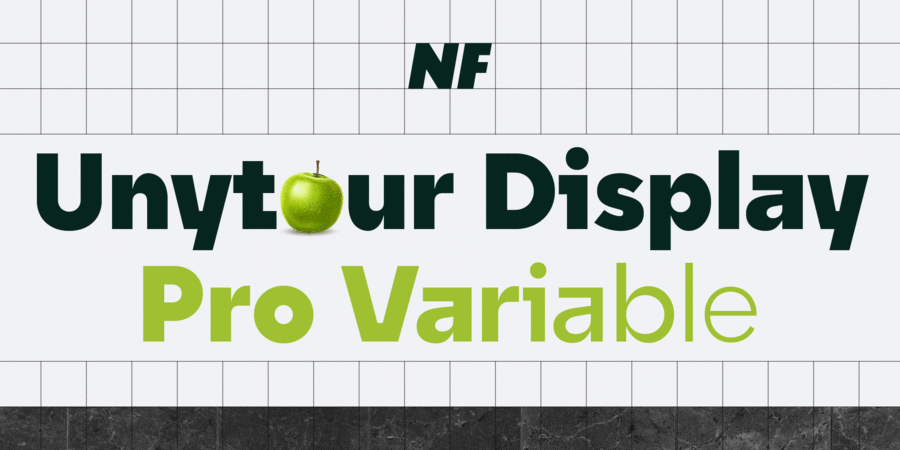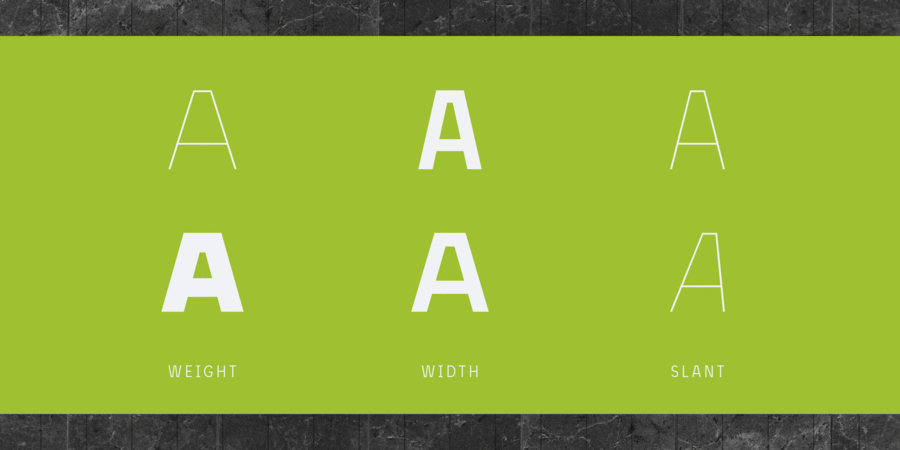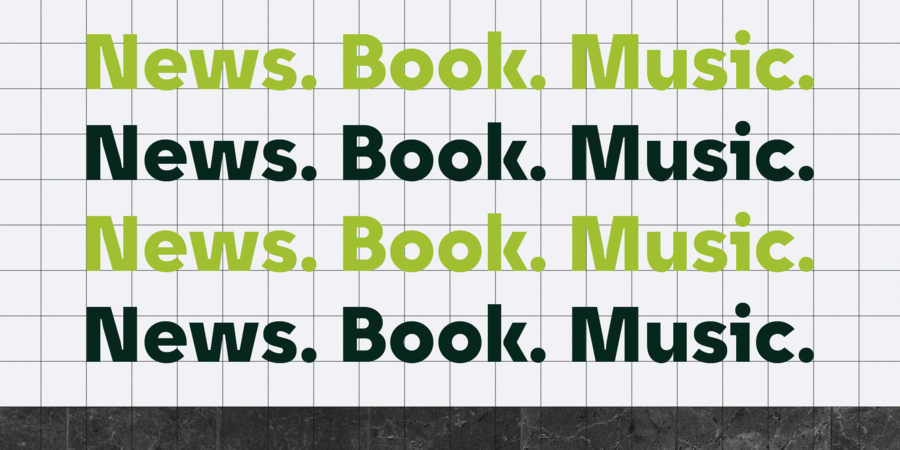
Опис шрифта Unytour Display Pro VariableШрифт Unytour Display Pro Variable – сучасне доповнення до гарнітури Unytour Display Pro. Варіативний шрифт містить 3 осі: Вага (Weight), Ширина (Width), Нахил (Slant). Завдяки технології варіативних шрифтів, Unytour Display Pro Variable надає дизайнерам гнучкість у роботі. Ви з легкістю можете налаштовувати параметри насиченості, ширини та нахилу, щоб досягти ідеального балансу та гармонії візуального стилю для свого проєкту.
Шрифт містить альтернативні гліфи для таких символів, як A, G, I, R, a, l, t, y, що додає вашій типографіці особливого характеру та індивідуальності. Крім того, багатий набір OpenType-функцій значно розширює ваші творчі можливості. Unytour Display Pro Variable має гарну читабельність як у друці, так і на екранах телевізорів та інших пристроях. Шрифт розробив Микола Савчук у 2024 році. Особливості сімейства шрифтів Unytour Display Pro VariableХіт десятиліття:
Асоціації з сімейством шрифтів Unytour Display Pro VariableОсобистість і характер гарнітури:
твердий, надійний, точний, впевнений, сталевий, рівний, стійкий, холодний, машинний, гострий, урбаністичний, міський, скляний, крижаний, ламаний, оригінальний, квадратний, експериментальний, дзвінкий, сміливий, кутастий, рубаний, чіткий, дивний, характерний, незвичайний, модний, цікавий